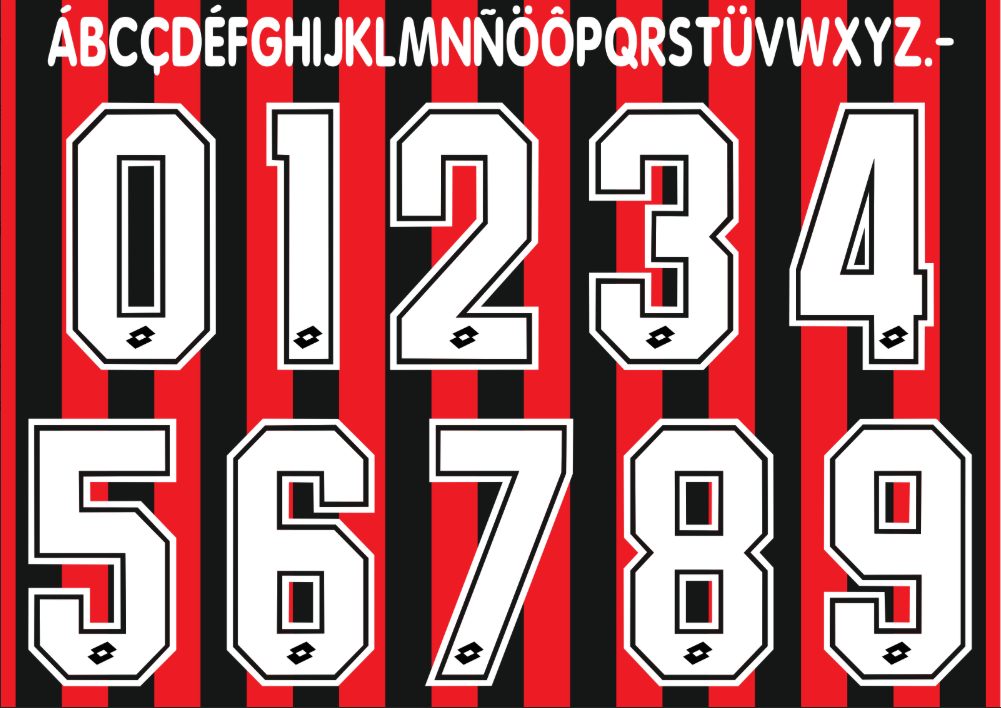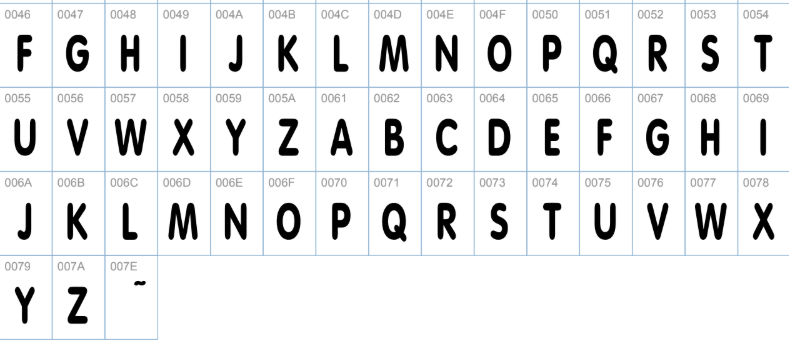
Se existe uma época que define a elegância do futebol italiano, é a metade dos anos 90. O AC Milan, vestido pela Lotto, desfilava pelos gramados da Europa com um elenco galáctico: George Weah, Roberto Baggio, Maldini e Savicevic.
Para os amantes do design retrô e colecionadores, disponibilizamos a fonte exata utilizada nas camisas Rossoneri durante as temporadas de 1995 a 1998. É a tipografia que marcou o scudetto de 96 e a inesquecível camisa com o patrocínio da “Opel”.
Este arquivo foi digitalizado com base nos uniformes originais da época (“match worn”), garantindo fidelidade absoluta para restaurações e projetos vintage.
- Conteúdo: Numeração clássica (com o logo da Lotto na base, se aplicável no vetor) e alfabeto completo.
Estilo Visual da Tipografia
A fonte desenvolvida pela Lotto para o Milan nos anos 90 é um ícone do design esportivo daquela década. Ela apresenta um estilo Block Shadow (blocado com sombra projetada), que dava um efeito 3D muito característico nas costas das camisas.
Os números são robustos e largos, transmitindo a solidez da defesa milanista da época. A aplicação original geralmente era feita em plástico termo-adesivo aveludado (flock), e este arquivo digital reproduz os contornos exatos para que você possa simular essa textura em seus projetos digitais ou cortar o vinil com precisão.